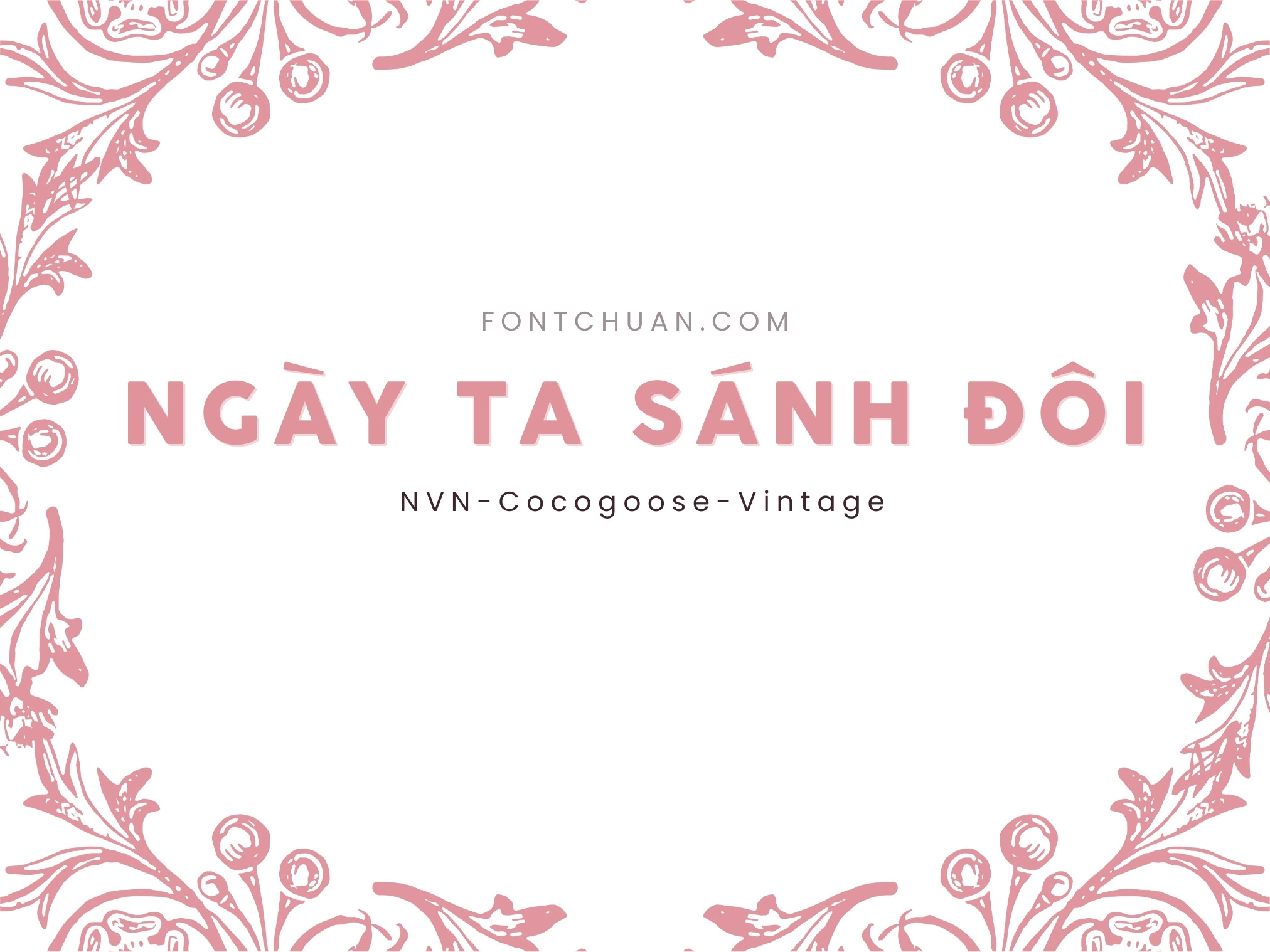
Cocogoose là một font chữ sans-serif hình học được thiết kế bởi Cosimo Lorenzo Pancini và phát hành bởi Zetafonts. Font này lấy cảm hứng từ nghệ thuật vẽ biển hiệu và lý tưởng hiện đại, được xây dựng trên cấu trúc sans cổ điển với các góc bo tròn nhẹ và điều chỉnh thị giác tinh tế. Với độ tương phản thấp, màu sắc đậm và chiều cao x cao, Cocogoose là lựa chọn mạnh mẽ cho các nhà thiết kế tìm kiếm một font chữ hiển thị ấn tượng cho logo, tiêu đề và thương hiệu mang phong cách cổ điển. Phiên bản Cocogoose Vintage đã được Việt hóa bởi NVN Font, hỗ trợ đầy đủ các ký tự tiếng Việt, mang lại trải nghiệm gõ chữ trọn vẹn cho người dùng Việt Nam. Ngoài tiếng Việt, font còn hỗ trợ hơn 200 ngôn ngữ khác, mở rộng khả năng ứng dụng trong các dự án quốc tế. Việc Việt hóa này được thành viên của Font Chuẩn chọn lọc và sưu tầm, nhằm đáp ứng nhu cầu bạn đọc và ứng dụng thực tế vào các dự án thiết kế.
Về đặc điểm thiết kế, Cocogoose có cấu trúc chữ hình học với các góc bo tròn nhẹ, tạo cảm giác mềm mại nhưng vẫn hiện đại. Độ tương phản thấp và chiều cao x cao giúp font dễ đọc ở các kích thước nhỏ, trong khi trọng lượng đậm của phiên bản Regular tạo ấn tượng mạnh khi sử dụng cho thương hiệu, biển hiệu hoặc font chữ trang trí. Với những đặc điểm trên, Cocogoose phù hợp cho các ứng dụng như thiết kế logo, tiêu đề, thương hiệu lấy cảm hứng cổ điển, biển hiệu và các dự án sáng tạo khác. Font này cũng có thể kết hợp với font valentine để tạo các thiết kế lãng mạn, tinh tế như thiệp Valentine hoặc poster dịp lễ tình nhân, hoặc có thể ứng dụng làm Font chữ Halloween cho các dự án mang không khí Halloween vui nhộn và độc đáo. Về ngành nghề, Cocogoose đặc biệt phù hợp với lĩnh vực quảng cáo, công nghệ, giáo dục và các ngành nghề cần sự sáng tạo và hiện đại trong thiết kế. Sự linh hoạt và tinh tế của font giúp nó dễ dàng hòa nhập vào nhiều phong cách thiết kế khác nhau, từ cổ điển đến hiện đại.